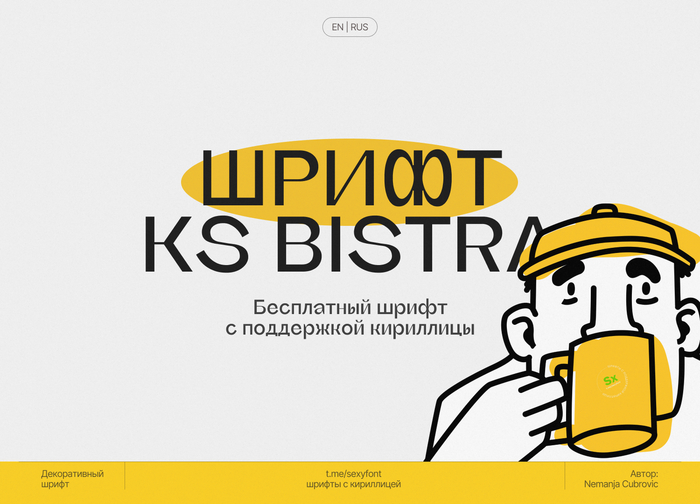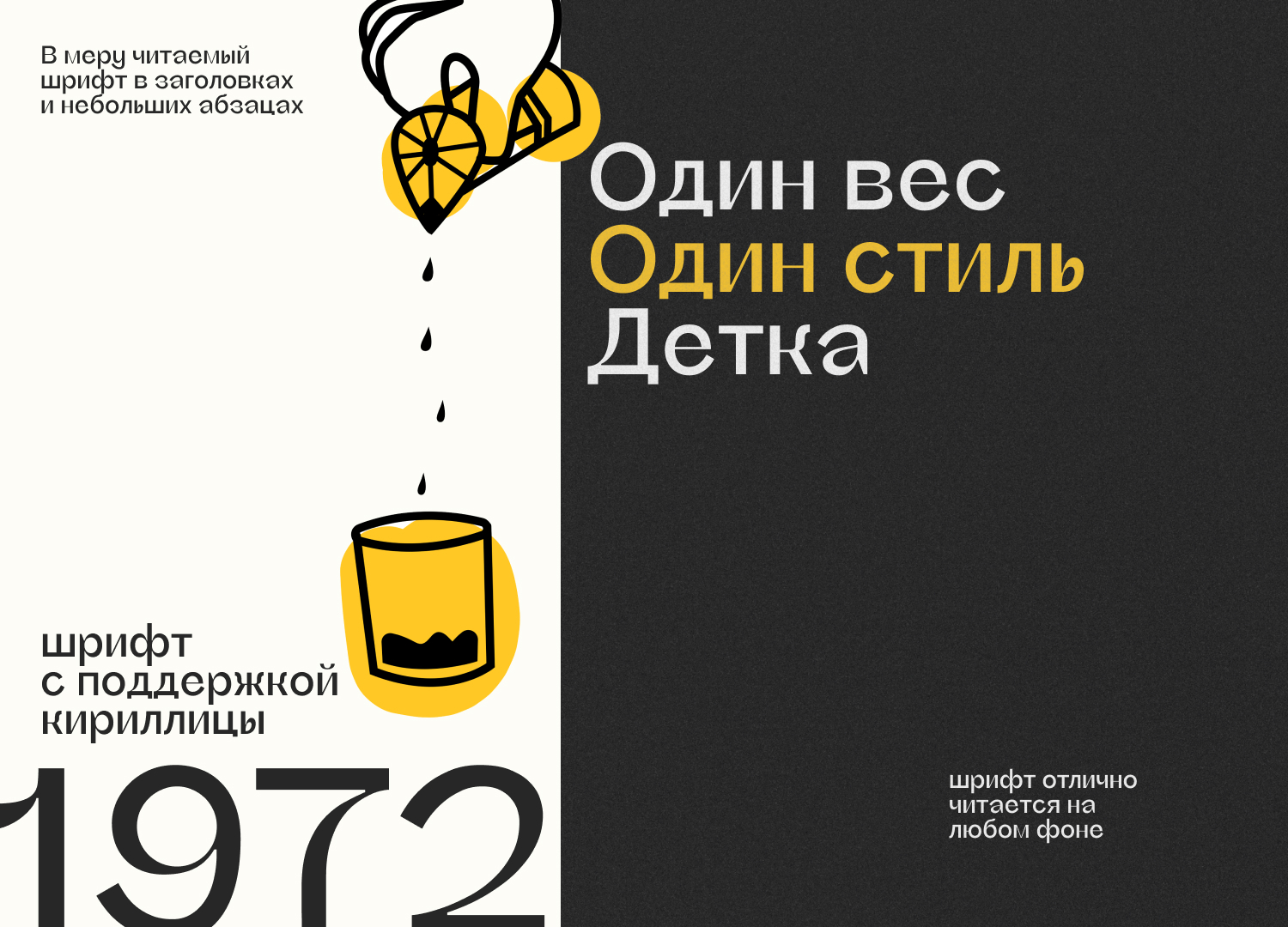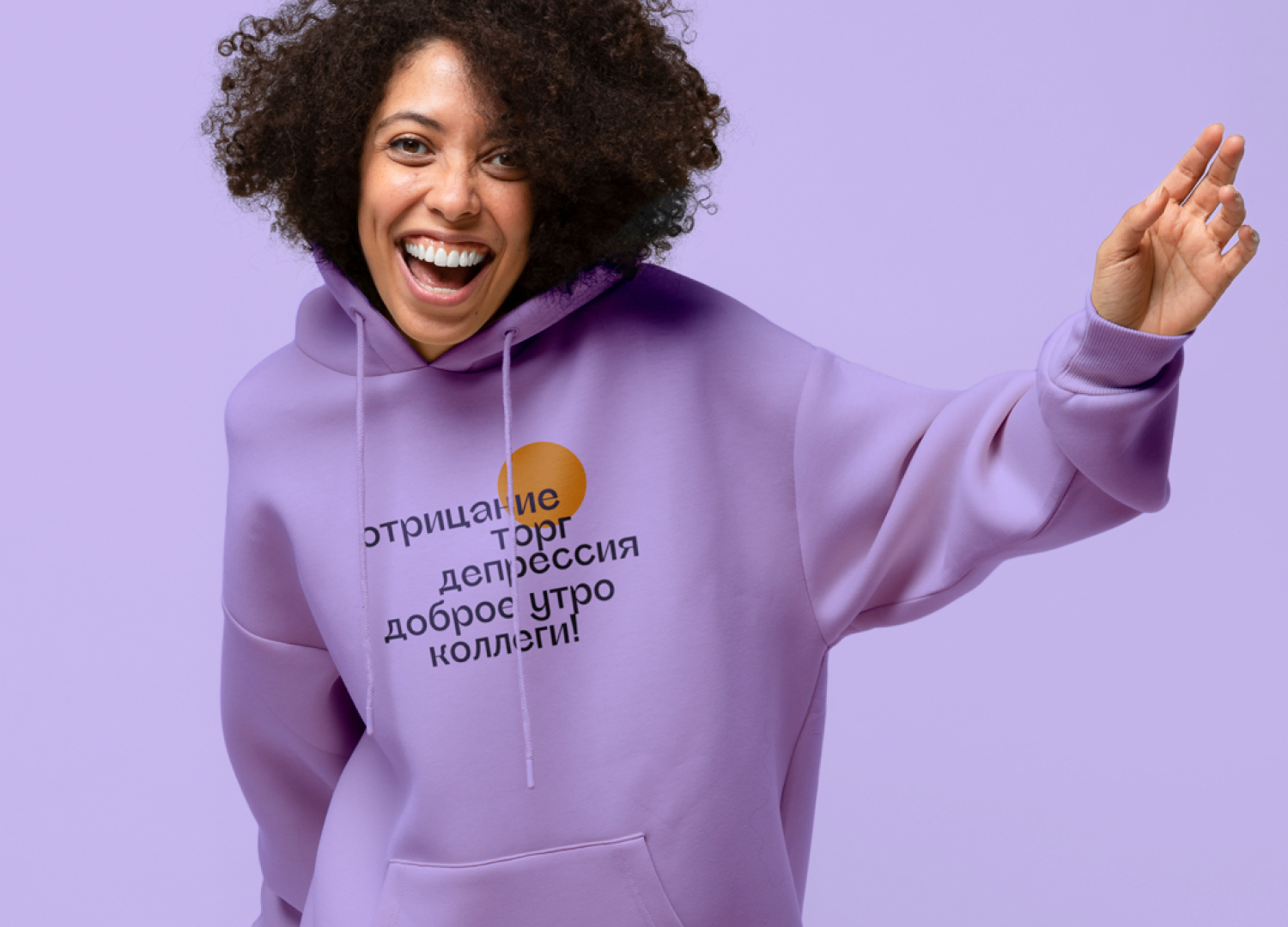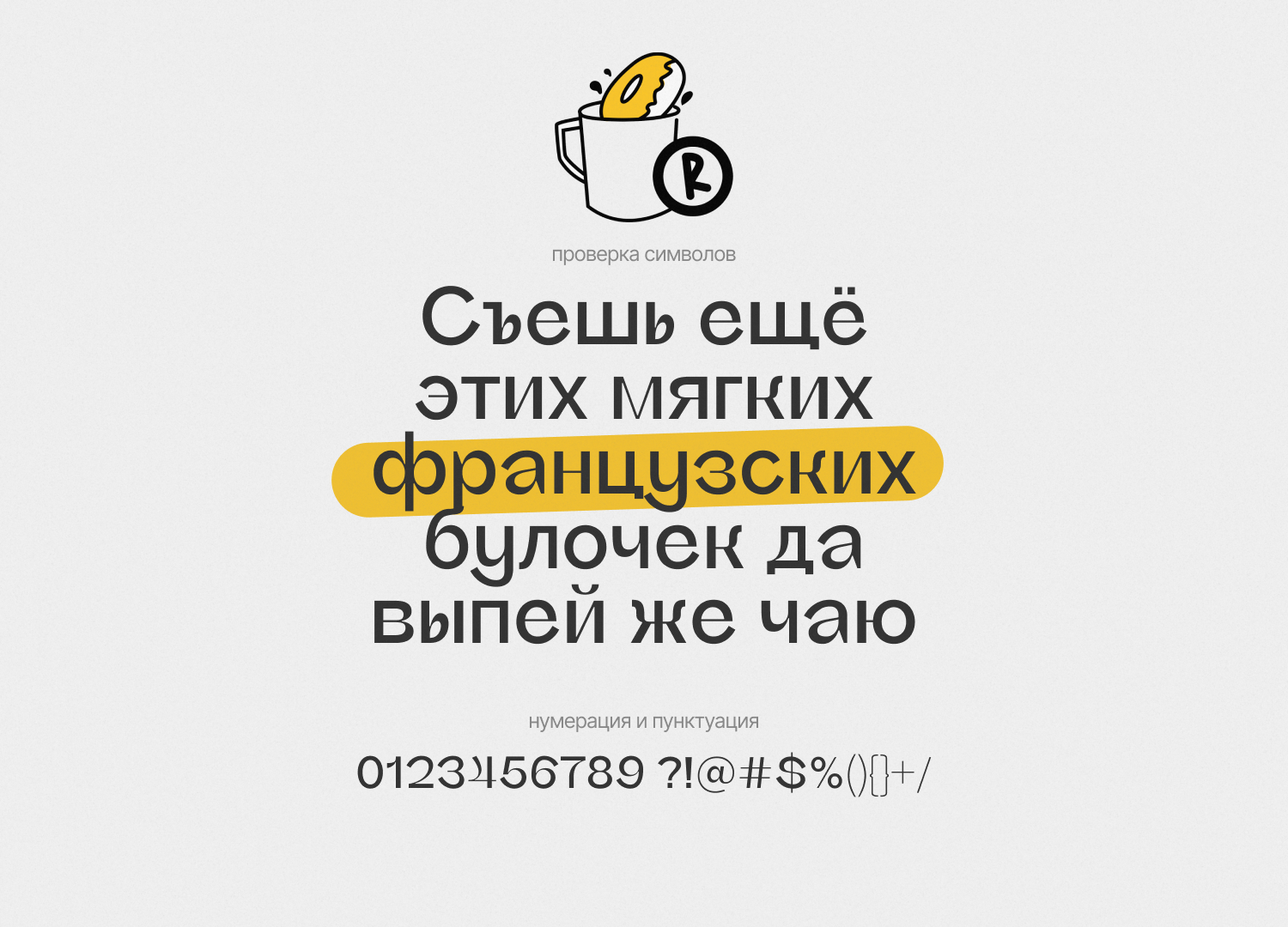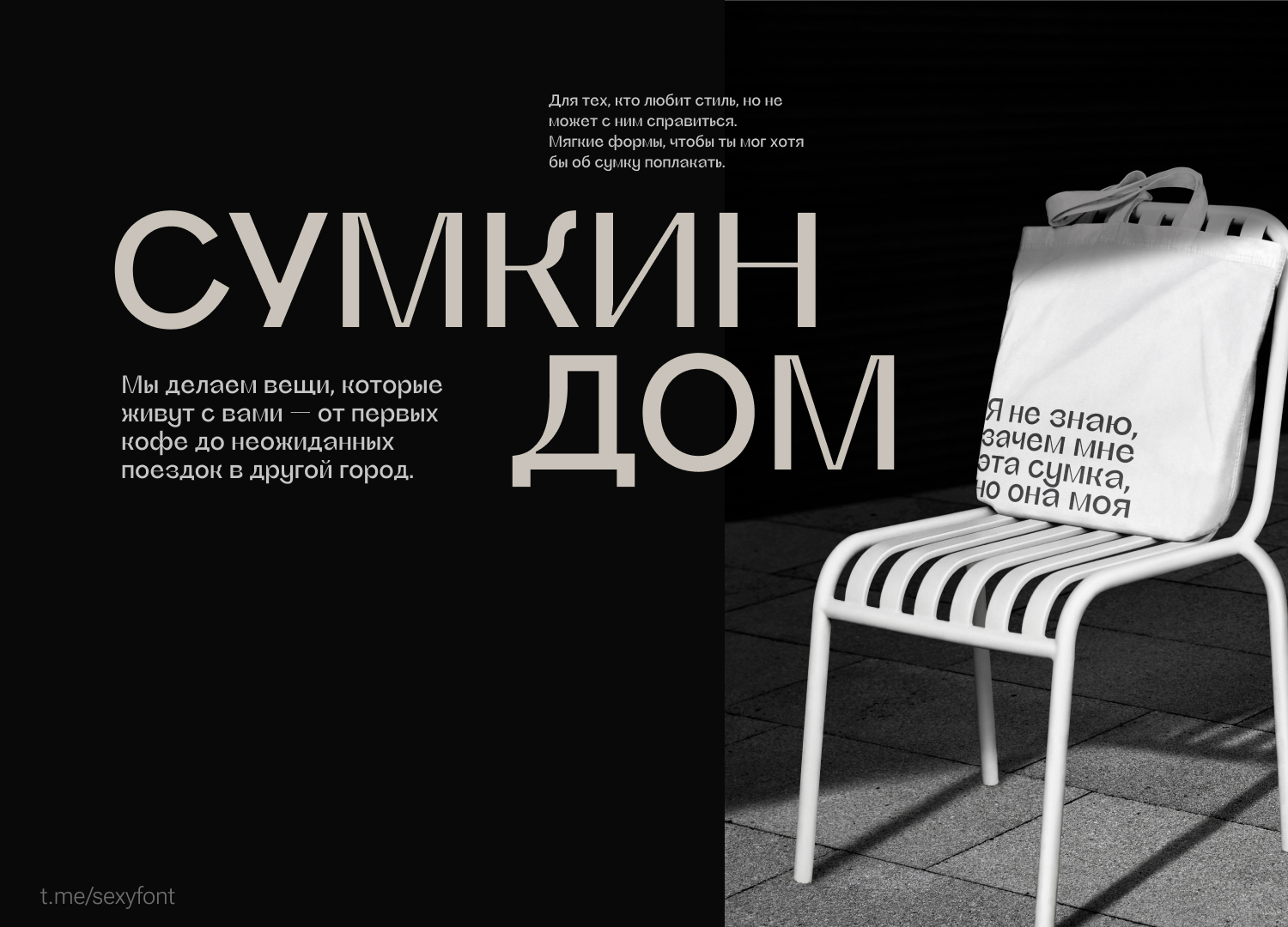
Бесплатный шрифт KS Bistra
Шрифт KS Bistra. Кириллический модерн с повадками журнального заголовка. Полугротесковый (semi‑grotesque) шрифт с нетипичным контрастом. Он смешивает элементы естественного и обратного контраста в рамках гуманистичной структуры